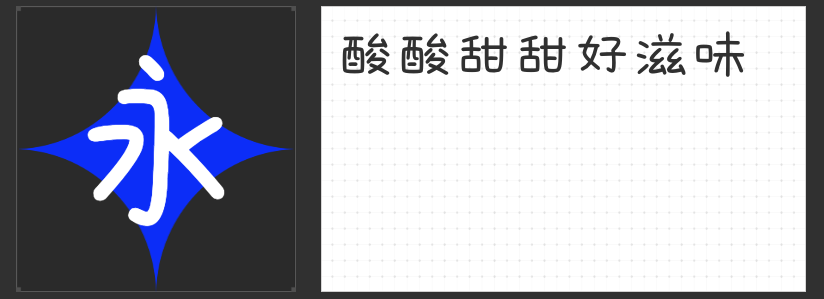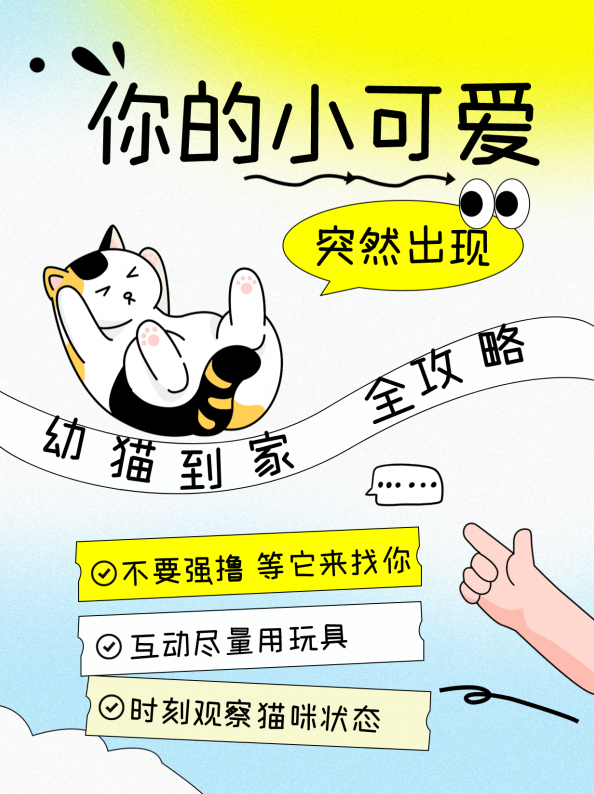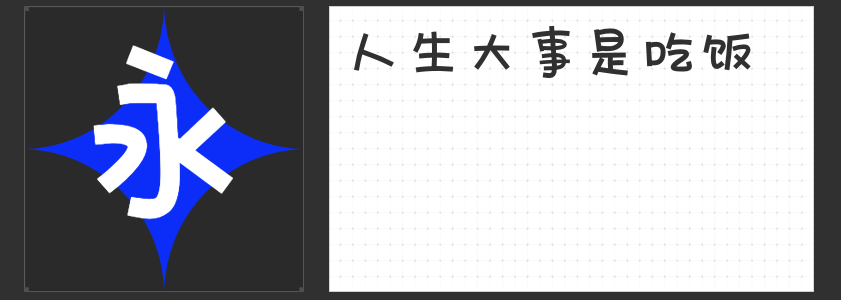
为设计注入灵动生☆命☆力!四款圆润字体推荐🙌
在视觉设计中,字体的选择直接影响作品的情感表达与氛围营造。今日推荐四款轮廓圆滑、充满创意的字体,它们以独特的笔画语言,为品牌标识、海报标题或包装设计注入鲜活个性。
一、字圈也字果酱体
灵感源于果酱的流动质感,这款字体以“横斜竖直”的骨架构建出叛逆的秩序感。折笔处钝角与直角的交替,搭配时而圆润、时而尖锐的棱角,如同果酱在瓶中蜿蜒的轨迹,传递出“不迎合世俗”的自信态度。其粗细对比强烈的笔画与左低右高的视觉重心,尤其适合需要展现年轻活力的食品、潮玩品牌设计。
二、高手庆科可爱体
以直线为骨骼,圆角为血肉,这款字体将手写体的稚拙感与现代审美巧妙融合。去钩化处理的竖弯钩与均匀的内部留白,既保留了手写痕迹的亲切感,又确保了小字号下的易读性。横竖笔画等粗的设计,使其在儿童教育、文创周边等场景中,既能传递温暖,又能保持版面整洁。
三、励字光明简 超黑
作为一款超粗黑体,其全部笔画以饱满弧线构成,仿佛阳光穿透云层的轨迹。横画结尾的斜切处理与口字部的斜角设计,在厚重中注入锐利感,赋予标题强烈的视觉穿透力。开阔的字心与均匀灰度,使其成为户外广告、科技品牌主视觉的优选,兼具专业感与现代节奏。
四、字圈也字花卷体
与果酱体同源却性格迥异,花卷体以中式面点为灵感,通过横斜竖直的骨架与折笔处的钝角处理,模拟面团发酵时的自然形态。棱角的圆润与尖锐交替,如同面点师指尖的揉捏痕迹,传递出“外柔内刚”的东方智慧。这款字体尤其适配餐饮、传统文化类设计,在圆润中暗含筋骨。
四款字体虽风格各异,但均以圆滑轮廓打破刻板印象。灵活组合使用,可让设计在圆润基调中绽放多元魅力。